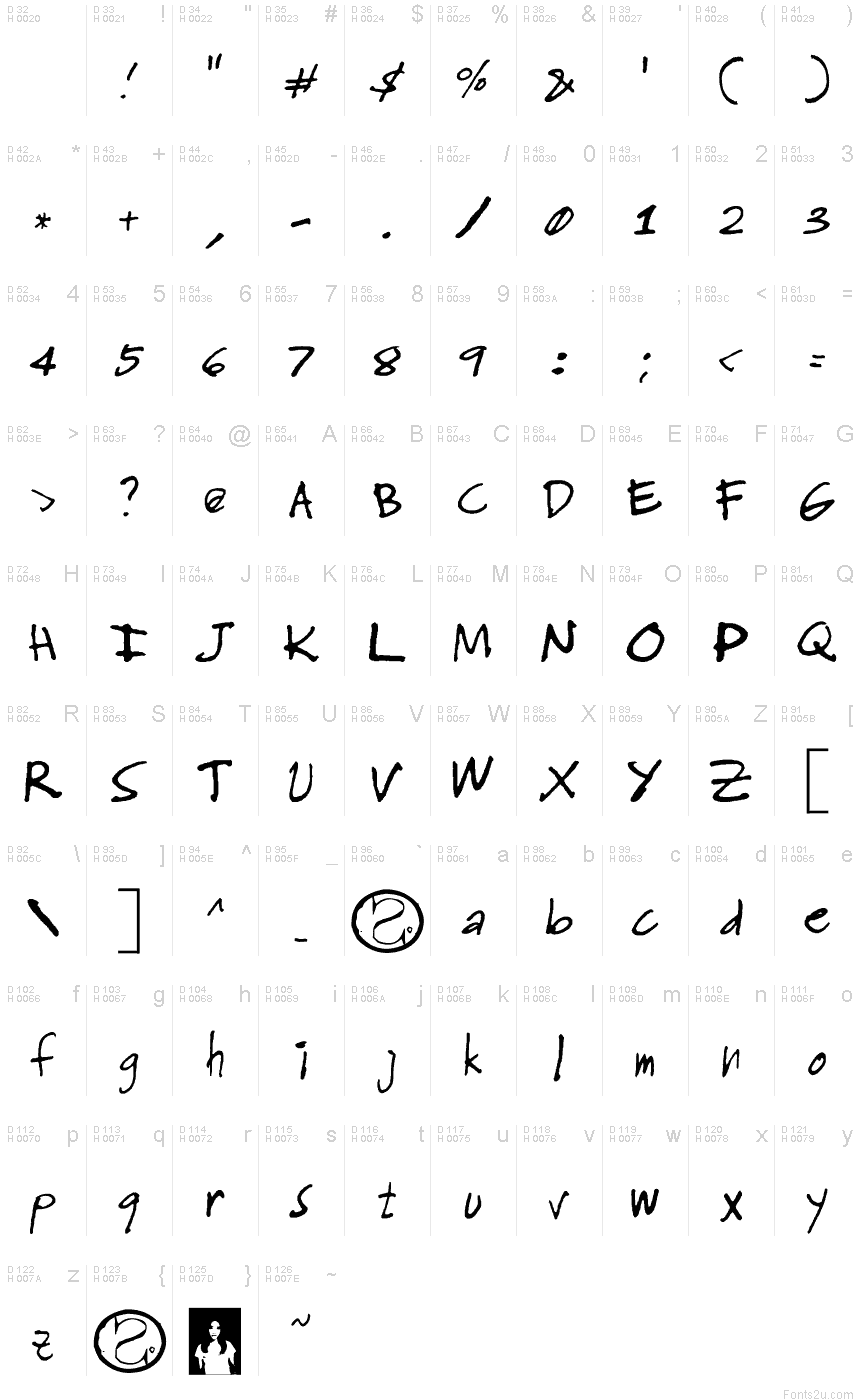
James Tan Dinawanao od Dinawanao Bhambie je bezplatné rukopisné písmo se syrovým, drsným charakterem, který působí, jako by vypadlo přímo ze stránek chaotického skicáře. Jeho vysoké, roztřesené tahy a inkoustová textura připomínající graffiti dodávají každému slovu pocit neklidného pohybu, jako by bylo narychlo načrtnuto silným fixem. Rozestupy jsou záměrně volné a nepravidelné, což vytváří neuhlazenou, pouliční energii, která okamžitě upoutá pozornost.
S James Tan Dinawanao získáte rukopisný styl, který prosperuje v chaosu. Je to přirozená volba pro ziny, hororové či thrillerové plakáty, letáky undergroundové hudby, výraznou grafiku na sociální sítě, branding skate nebo streetwear značek či titulky expresivních deníků. Toto bezplatné písmo nejlépe vynikne ve velkých, tučných velikostech, kdy naplno vyniknou jeho drsné obrysy a cákance. Zkombinujte ho s čistým, jednoduchým bezpatkovým písmem v hlavním textu, abyste zachovali čitelnost a zároveň si udrželi jeho divoký, ručně kreslený hlas.